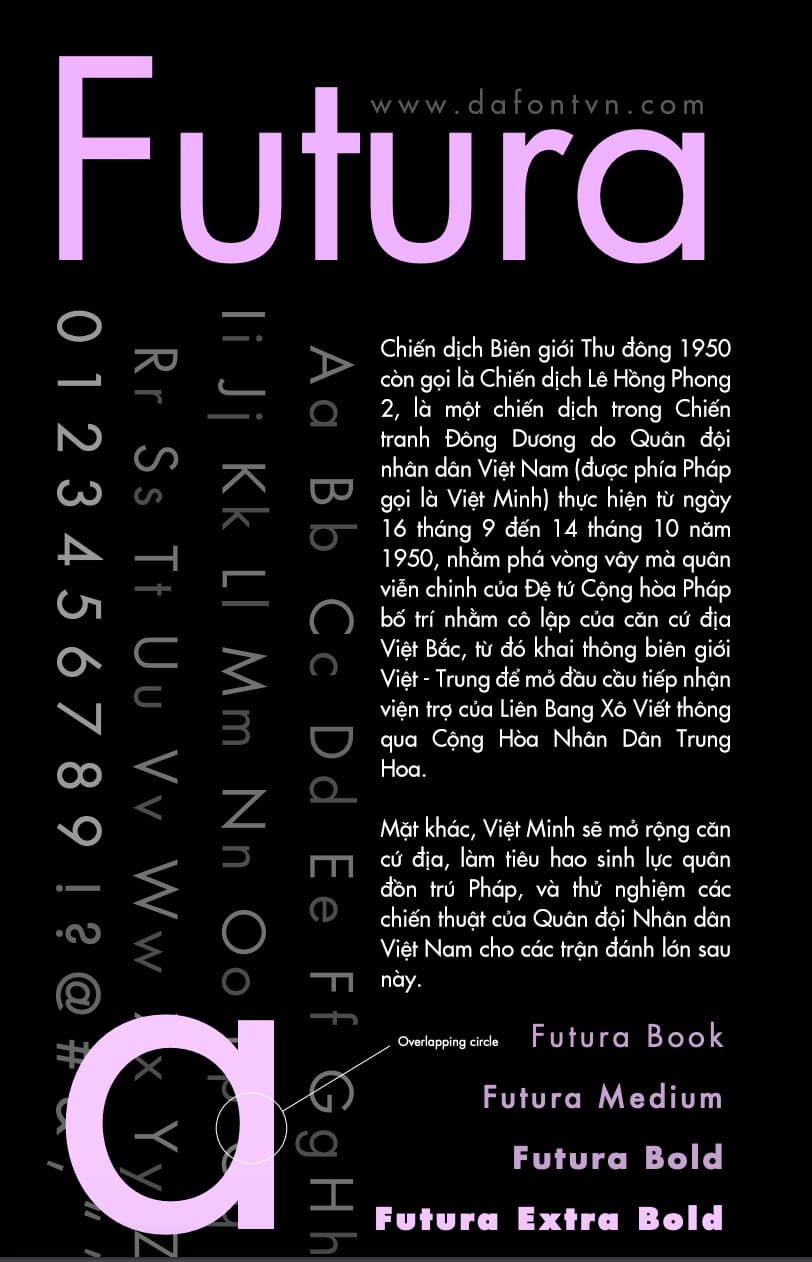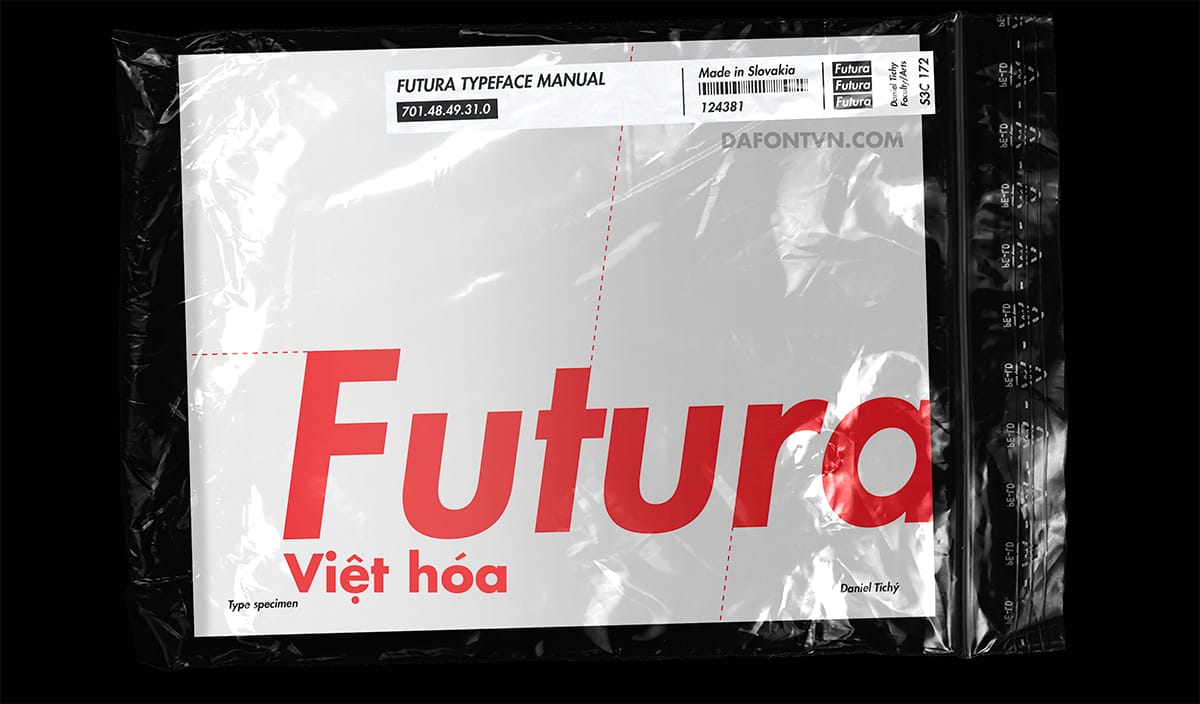
được coi là sự phát triển kiểu chữ chính xuất phát từ định hướng Kiến tạo của
phong trào Bauhaus ở Đức.
Paul Renner (nhà thiết kế, họa sĩ) đã phác thảo các
bản vẽ ban đầu và dựa trên các dạng đơn giản của hình tròn, hình tam giác và
hình vuông. Văn phòng thiết kế tại Bauer đã hỗ trợ ông biến những dạng hình học
này thành một họ kiểu font hoạt động mạnh mẽ, và theo thời gian, Renner đã thực
hiện những thay đổi để làm cho font chữ Futura trở nên dễ đọc hơn.
Cho dù
font Futura Việt Hóa
đã ra đời từ rất lâu nhưng cho đến nay Futura vẫn là
một trong những font chữ được sử dụng rộng rãi trên khắp thế giới.